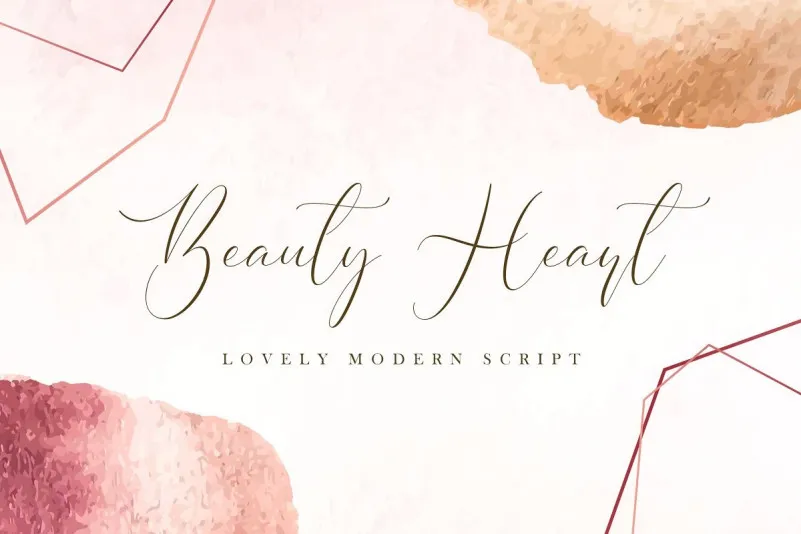
Beauty Heart Script Font – Download Grátis
A ‘Beauty Heart Script Font’ é uma elegante caligrafia que também tem um toque atraente e contemporâneo. Esta fonte é perfeita para designers modernos, tanto para uso pessoal quanto comercial. Ela foi projetada para assegurar que sua marca ou evento se destaque, oferecendo personalidade com sofisticação. Ideal para aplicar em anúncios de moda, convites de casamento, cartões de negócios, logomarcas e até mesmo para trabalhos de caligrafia. Esta fonte vem com um conceito único, combinando elegância com criatividade e originalidade. O designer Hamilton criou uma peça de arte que será perfeita para quem busca algo especial e versátil na sua coleção de fonts. Não hesite em explorar a ‘Beauty Heart Script Font’ – certamente irá enriquecer seus projetos gráficos com um toque único e sofisticado.